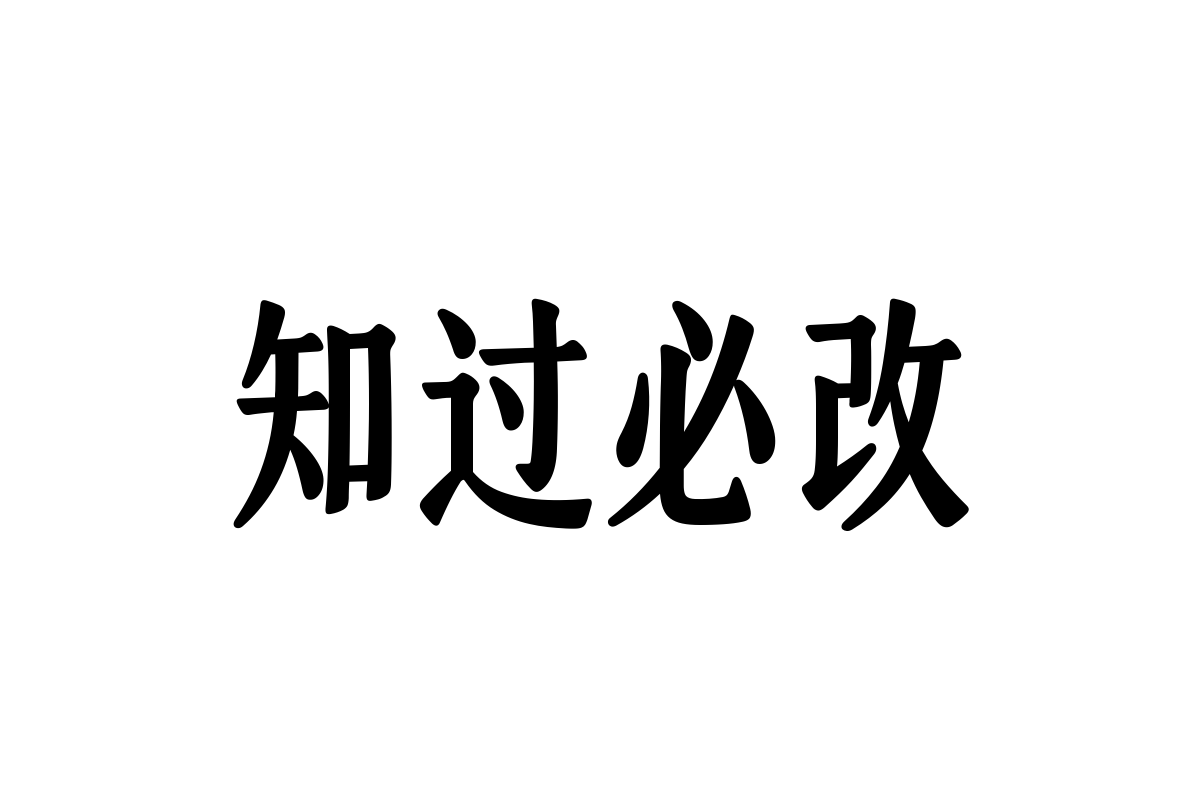
汉仪婉风宋是一款具有独特风格和特点的字体。它采用了传统的书法元素,结合现代设计,创造出一种既有传统韵味又不失现代感的字体。这款字体适用于各种需要书写或设计的场景,如广告、宣传册、海报、网页等。
汉仪婉风宋的特点如下:
1. 字形优美:这款字体的笔画流畅,结构紧凑,给人一种优雅的感觉。它的字形既适合用于正式场合,也适合用于创意设计。
2. 风格独特:汉仪婉风宋融合了传统书法的元素,使得字体具有独特的艺术风格。它的笔画粗细变化丰富,线条流畅自然,给人一种古朴典雅的感觉。
总之,汉仪婉风宋是一款具有独特风格和特点的字体,适用于各种需要书写或设计的场景。它不仅具有优美的字形,还具备易于使用和兼容性强的特点,是一款值得设计师们尝试的字体。